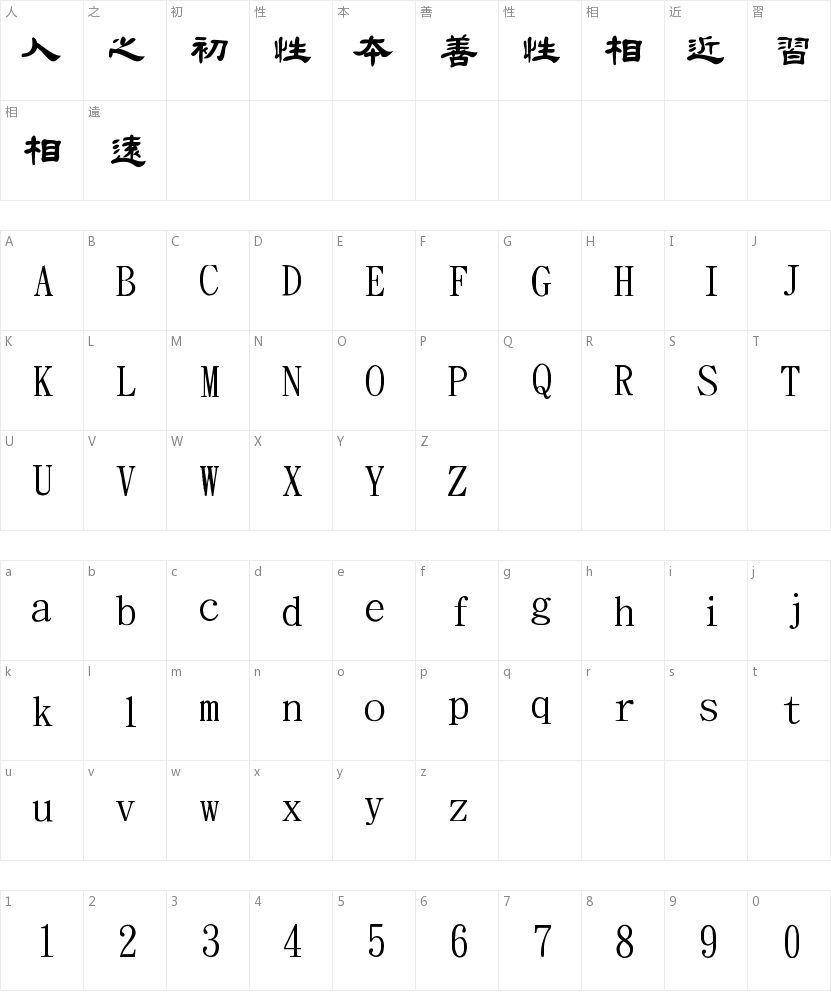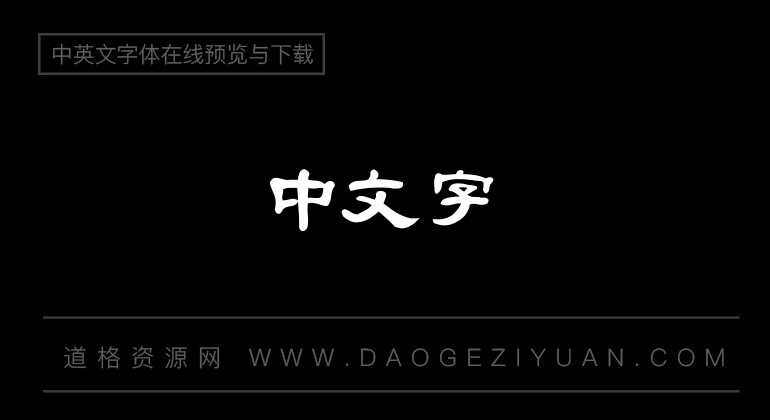
金梅毛隸書國際碼是一種中文字體,它是由英國設計師和中國字體專家共同開發的,是一款結合了中國傳統毛筆書法和西方文字設計的字體。它具有傳統毛筆書法的精細筆劃和清晰的結構,融合了西方文字設計的細節,使得文字更加精緻,更有質感。它也支持多種語言,可以用於各種文字網頁設計,書籍設計等等。內容介紹
金梅毛隸書國際碼是一款非常不錯的手寫藝術字體,具有很好的視覺感,適合於文化類的宣傳設計、商業類品牌的廣告和產品包裝設計以及個性化文字排版等較多場景。